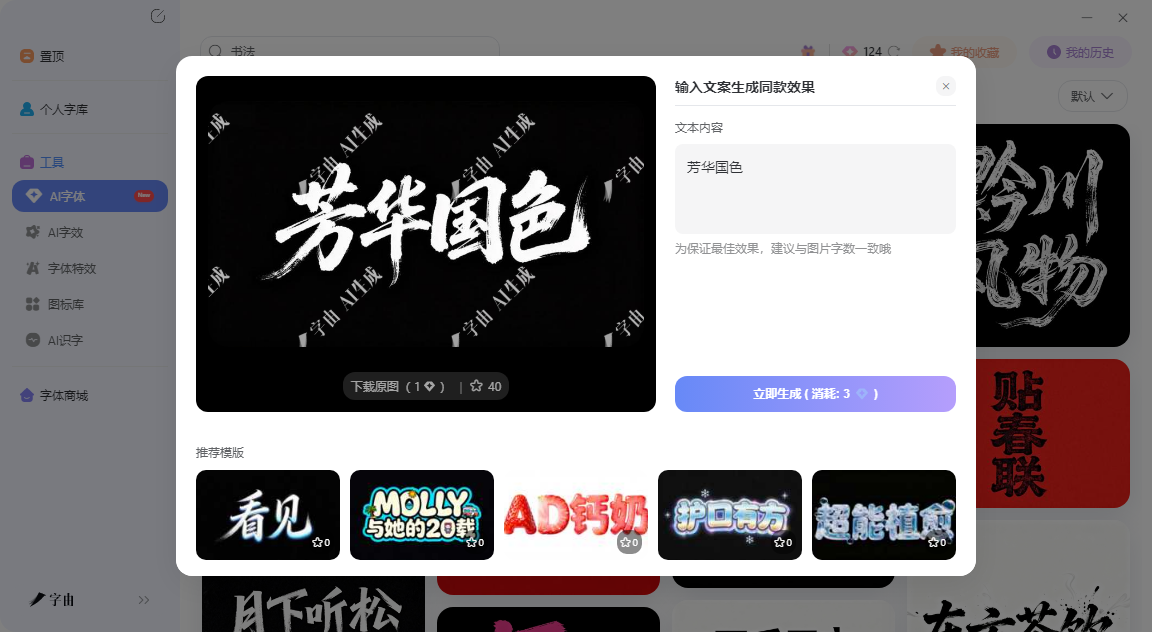
在线书法字体生成不用愁,字由帮你一键搞定
在聊工具之前,不妨花半分钟想清楚一个问题:你这次需要的是“某个字的特定写法”,还是“一款能反复用的书法字体”?这两种需求差别很大。如果你只是给一张海报做一个标题,你需要的是书法字图片,可能只需要一次性生成;如果你是给一个品牌做Logo,以后还要做包装、做名片、做公众号头图,你需要的是书法字体,要能反复打出不同的字。字由恰好同时覆盖了这两种需求——AI字体负责出图,字体库负责出字体。下面按这三种方式拆开讲。
1、方式一:AI字体
如果你的需求是做一张现成的书法字图片,放海报、封面、Banner上用,AI字体是最快的路子。打开字由客户端,在左侧导航栏找到〖工具〗→〖AI字体〗。进去之后会看到一个模板库,目前提供了400多种特效模板,其中专门有一大类是“书法风”和“国潮风”。
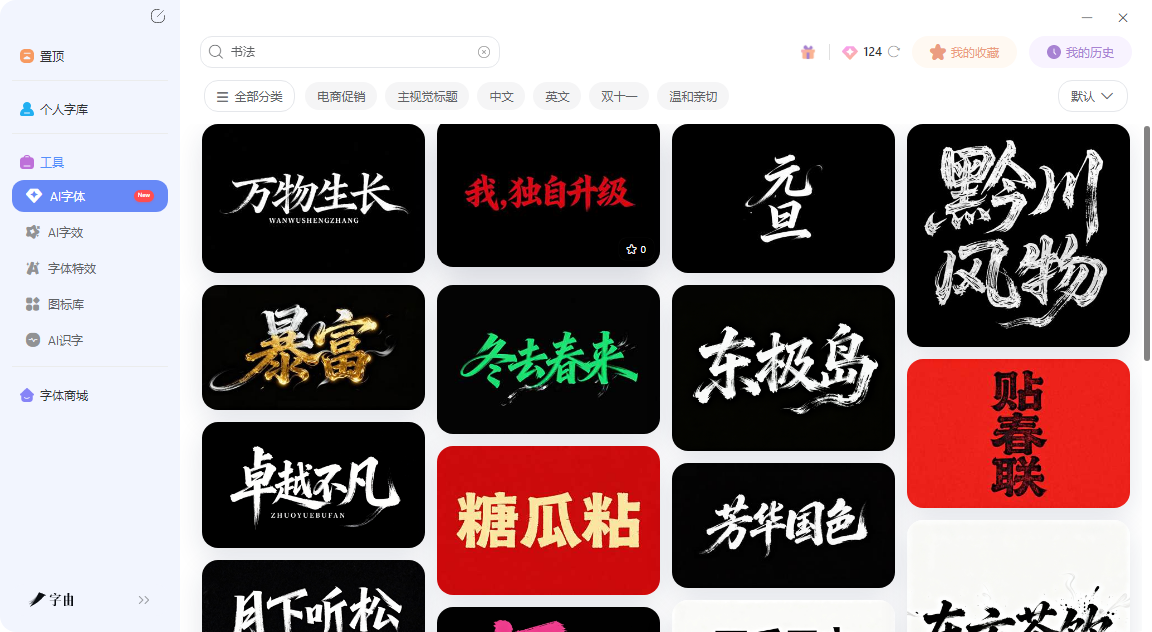
操作就三步:选模板、改文字、生成。
- 第一步,在左侧筛选栏里点“国潮风”或“书法风”,所有书法相关的模板会一次性列出来。模板预览图里会展示效果——有的偏水墨晕染,有的偏鎏金质感,有的像碑刻拓印,有的像毛笔挥毫。鼠标滑过一个模板,预览图里会立刻用你预设的文字展示效果,不用点进去就能看到大概。
- 第二步,点“做同款”,在右侧输入框里填你的文案。这里有一个小细节:最好和模板原本的字数保持一致。如果模板是四个字,你也填四个字;如果模板是两个字,你就填两个字。字数不一致,生成出来的排版可能会歪。
- 第三步,点“立即生成”,等待25秒左右,系统就会输出设计好的书法字图片。生成后可以下载透明背景的PNG格式,直接拖进PS、剪映或者海报里就能用。每次生成消耗3个算力点,字由每天登录会赠送6个算力点,相当于每天可以免费生成2张图。日常设计完全够用。
模板里,书法风格的覆盖面非常广。想做国潮品牌标题,有“鎏金篆刻”“水墨丹青”这类传统风格;有“霓虹国潮”这种带灯管效果;想做新中式海报,有“锦绣华纹”这种融合纹样装饰的风格。这比较适合电商运营赶活动海报、自媒体做封面图、设计新手不会PS、或者只是想快速出一张书法标题图的人。
2、方式二:字体激活
如果你的需求不是出一张图,而是要长期、反复使用某款书法字体——比如给品牌做标准字,以后还要做包装、做名片、做Banner——那就走激活这条路。字由的字体库里收录了大量书法类字体,并且专门做了分类。打开字由客户端,在左侧筛选栏里找到“字体类型”,勾选“书法体”,上百款书法字体会一次性列出来。你还可以进一步细分为“楷书”“行书”“草书”“隶书”“篆书”等。
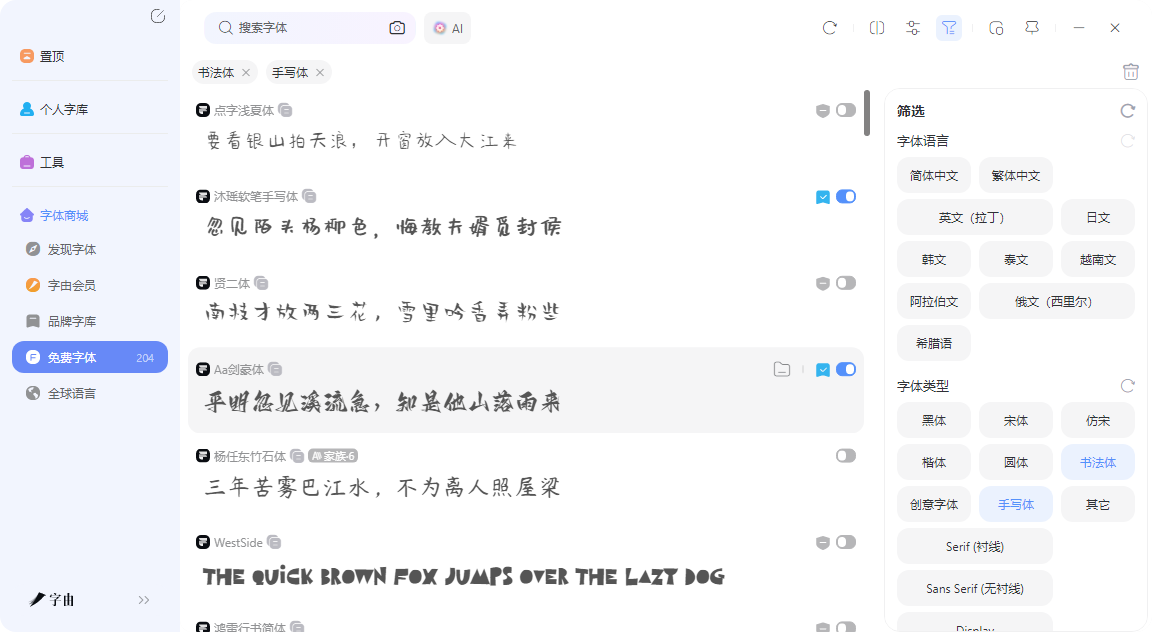
找到喜欢的字体之后,点击字体右侧的“激活”按钮(灰色对勾变绿),这款书法字体就“激活”了。然后打开你的PS、AI或Word,在字体下拉菜单里就能直接使用这款书法体,不需要下载安装包,不需要解压,不需要打开,也不用重启软件。
激活的好处是“一次设置,反复使用”。你今天给品牌做了一个Logo,用的是字由颜楷;下周做包装的时候,同样的字体点一下激活就能用,不用重新找。换电脑的时候,登录同一个字由账号,之前激活过的字体自动同步,不用每台设备重新激活。这个方法比较适合设计师做品牌VI、做系列海报、做需要统一字体的项目,以及任何需要长期使用同一款书法字体的人。
3、方式三:详情页预览
这是三种方式里最容易被忽略、但其实最实用的一个。它本身不算“生成”,而是“尝试”——在你决定激活某款书法字体之前,先在详情页里预览一下效果。打开字由客户端,点进任意一款字体的详情页,你会看到一个文字输入框。在框里输入你想要预览的文字,比如你的品牌名“长安赋”或者是“一叶知秋”,页面会实时切换成这款字体应用到你的文案上的效果。
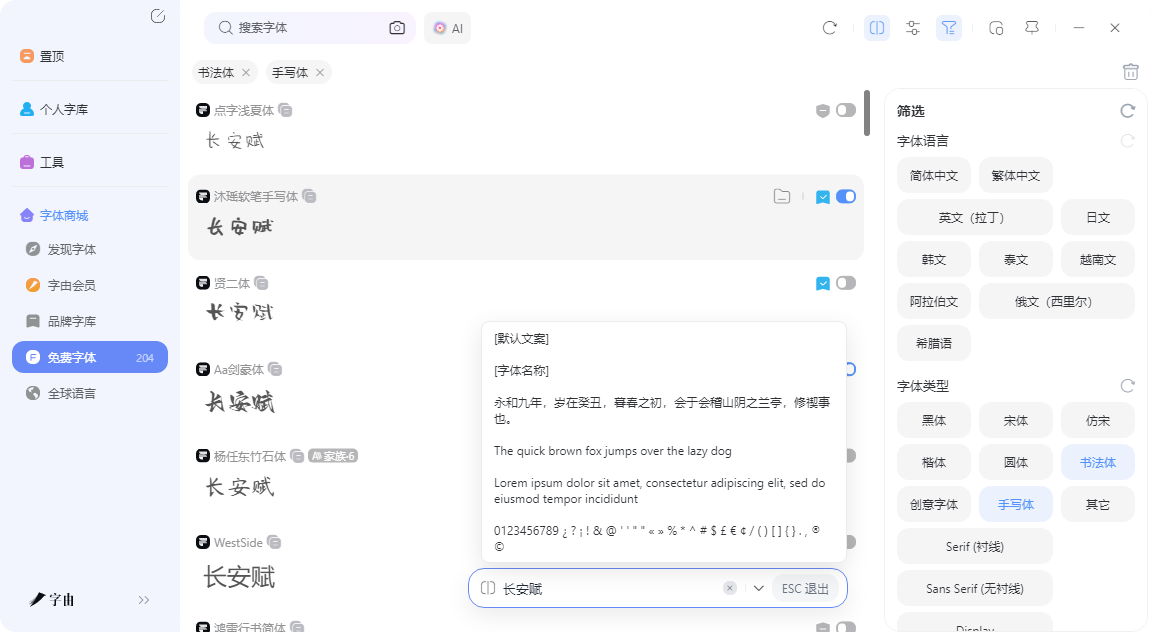
这个方法尤其适合需要大量试用书法字体的场景。比如你在做一个品牌VI,要在十几款候选楷书之间反复对比。每款都先激活再试太麻烦,直接在详情页里输入品牌名称,挨个看一遍效果,选中最满意的那一两款再激活,效率高很多。详情页里还会显示这款字体的授权类型——免费商用、会员商用、个人使用,一目了然。做商业项目的时候,每次先看授权信息再激活使用,不会踩版权坑。
这适合品牌VI选型期、需要对比多款书法字体的设计师、对字体适配度有要求的人。
4、其他实用的功能
- 热度排序:每款字体右侧都显示“使用次数”,这是基于平台上所有设计师的真实使用行为统计的。排在前面的,说明被大量项目验证过。反过来,按“热度从低到高”排序,可以专门挑那些小众、还没被用烂的宝藏书法体。
- AI识字:你在网上看到一张海报上的书法字特别好看,但不知道叫什么名字。用AI识字上传图片,3到5秒就能识别出字体名称和授权信息,直接点“激活”就能用。